Font Việt hóa Thư pháp Đại tự là kiểu chữ mang đậm phong cách thư pháp Á Đông, với nét bút mạnh mẽ, dứt khoát và giàu ý nghĩa truyền thống. Đây là lựa chọn lý tưởng cho các thiết kế liên quan đến Tết, phong thủy, văn hóa hoặc quà tặng mang giá trị tinh thần.
Font thư pháp đại tự Việt hóa nổi bật với nét chữ lớn, dày và mang tính biểu tượng cao, thường dùng cho các chữ như Phúc, Lộc, Thọ, Tài, Hỷ… Phiên bản Việt hóa đã được tối ưu đầy đủ dấu tiếng Việt, giúp bạn dễ dàng sử dụng mà không lo lỗi font. Font có thể sử dụng trên các phần mềm thiết kế như Photoshop, Illustrator, CorelDRAW hoặc trong Word, PowerPoint.
5 mẫu font Thư pháp Đại tự Việt hóa nổi bật
Font Thư pháp Việt hóa đại tự không chỉ đa dạng về kiểu dáng mà còn mang đậm tinh thần văn hóa truyền thống, phù hợp cho nhiều mục đích thiết kế như câu đối, banner Tết hay trang trí nghệ thuật. Dưới đây là những mẫu font tiêu biểu được sử dụng phổ biến hiện nay:
Tên font |
Đặc điểm |
Ứng dụng |
| FZ Đại Tự (FontZin) | Nét đậm, phóng khoáng, chữ to rõ |
Tiêu đề lớn, hoành phi, câu đối |
FZ Đức Thủy |
Nét uyển chuyển, mang phong cách đại tự |
Nội dung nổi bật, thiết kế nghệ thuật |
| UTM Thiên Ân | Phong cách cổ trang, trang nghiêm |
Thiết kế Tết, văn hóa truyền thống |
| Thư Pháp Quang Ninh | Nét viết tay sắc sảo, đậm chất ông đồ |
Poster, thiệp, trang trí nghệ thuật |
| Thành Công / Công Thủy | Nét chữ hoài cổ, mạnh mẽ |
Banner, tranh treo, câu đối |
Đặc điểm nổi bật của font Việt hóa Thư pháp Đại tự
Font Việt hóa Thư pháp Đại tự không chỉ gây ấn tượng bởi vẻ đẹp nghệ thuật độc đáo mà còn mang đậm giá trị văn hóa truyền thống, thể hiện tinh thần và ý nghĩa sâu sắc trong từng nét chữ:
- Nét chữ mạnh mẽ, dứt khoát: Mô phỏng bút lông truyền thống, tạo cảm giác uy nghi và trang trọng
- Đậm chất văn hóa Á Đông: Thường gắn liền với các giá trị may mắn, tài lộc, hạnh phúc
- Tính thẩm mỹ cao: Phù hợp trang trí và tạo điểm nhấn nghệ thuật
- Hỗ trợ tiếng Việt: Phiên bản Việt hóa giúp hiển thị đúng dấu, dễ sử dụng
- Phù hợp thiết kế lớn: Thường dùng cho chữ nổi bật, kích thước lớn
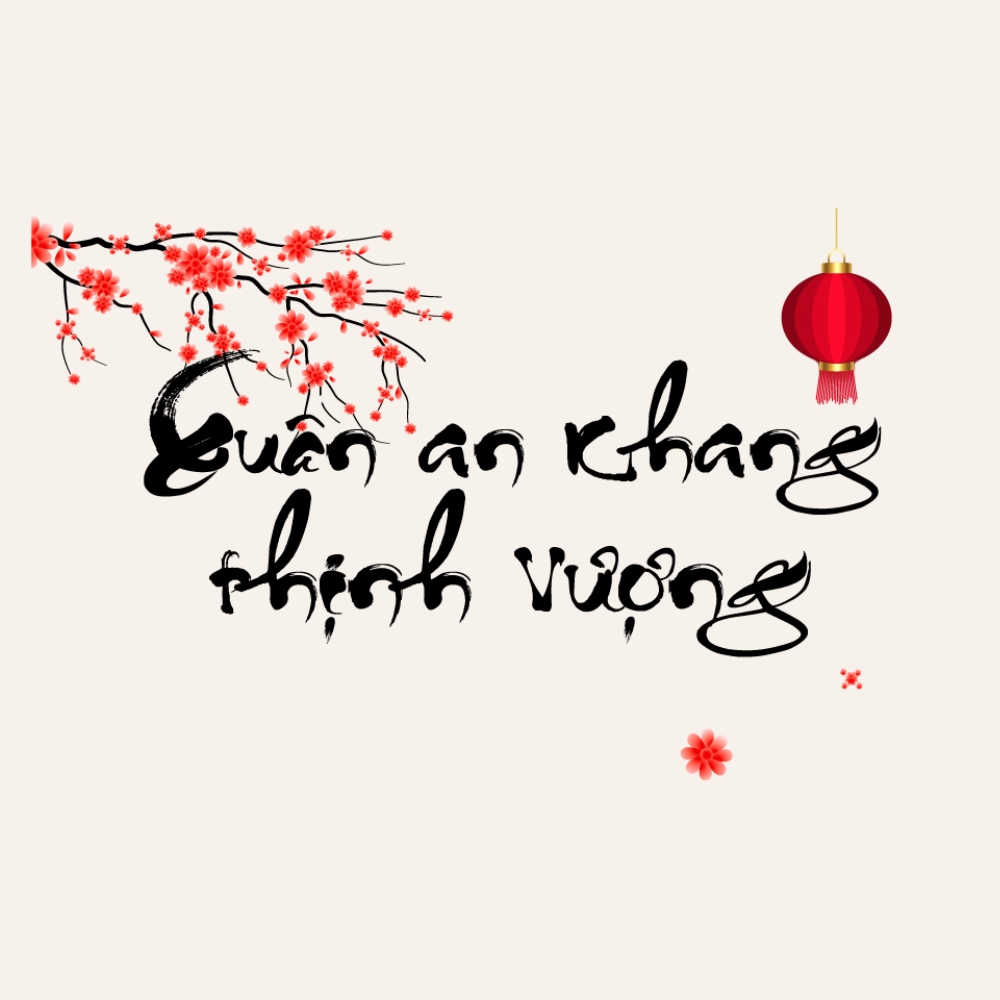
Ứng dụng của font Thư pháp Đại tự
Font Việt hóa Thư pháp Đại tự được ứng dụng nhiều trong:
- Trang trí Tết, câu đối, tranh treo tường
- Thiết kế bao lì xì, thiệp chúc mừng
- In ấn quà tặng doanh nghiệp dịp lễ, Tết
- Thiết kế backdrop sự kiện, banner
- Sản phẩm phong thủy, đồ lưu niệm
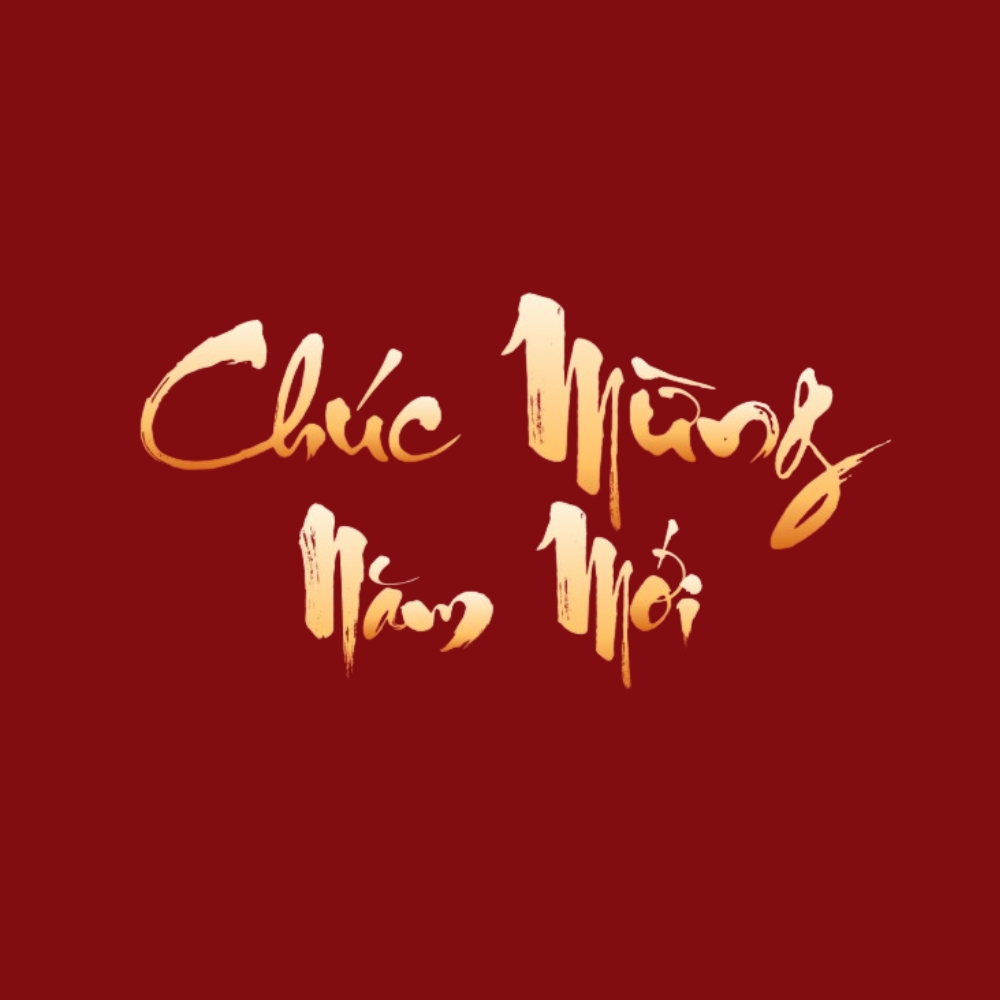
5 lưu ý khi sử dụng font Thư pháp Đại tự Việt hóa
Để khai thác tối đa tính thẩm mỹ và đảm bảo chất lượng khi thiết kế – in ấn, bạn nên lưu ý một số điểm sau:
- Phù hợp cho tiêu đề, không dùng cho nội dung dài: Font thư pháp đại tự thường có nét bay bổng, phức tạp nên chỉ phù hợp làm tiêu đề, slogan hoặc điểm nhấn. Tránh dùng cho đoạn văn dài vì sẽ gây khó đọc.
- Chọn kích thước lớn để thể hiện rõ nét thư pháp: Các font đại tự sẽ đẹp và ấn tượng hơn khi sử dụng ở kích thước lớn như banner, backdrop, tranh treo hoặc bao bì quà tặng.